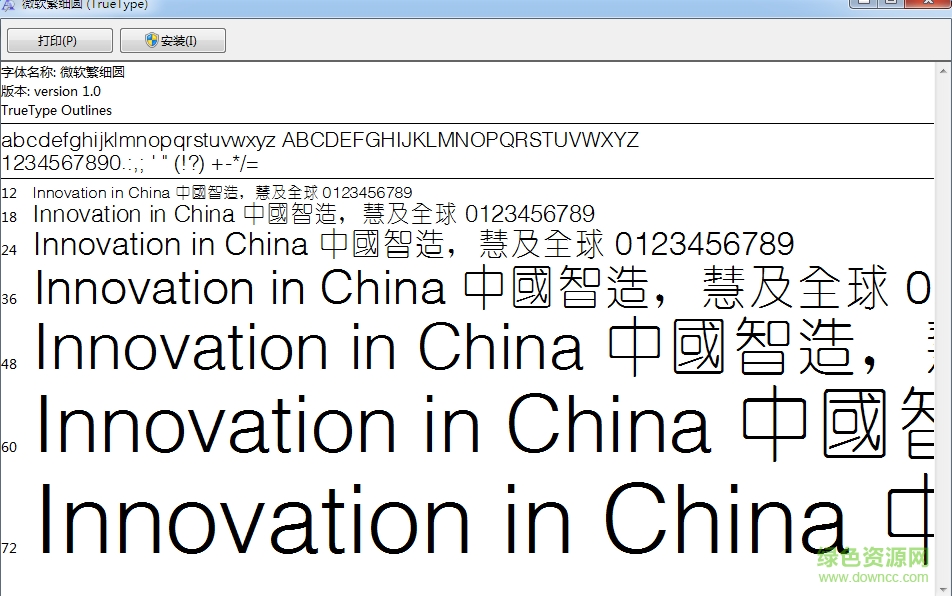
ctxiyuansf
ctxiyuansf字體是一款繁體的細(xì)圓字體,字體結(jié)構(gòu)嚴(yán)謹(jǐn),空隙均勻,撇捺舒展,纖美好看,適用于電子排版、平面設(shè)計(jì)或包裝設(shè)計(jì),需要的小伙伴趕緊來綠色資源網(wǎng)下載吧!
ctxiyuansf